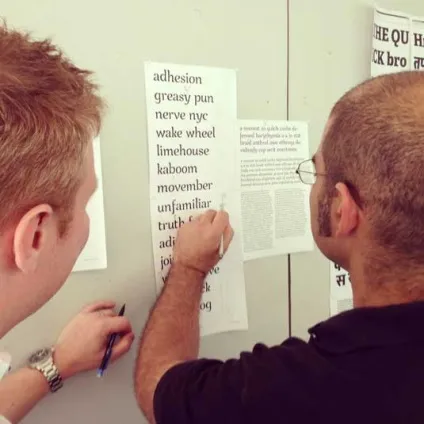
Як створити власний шрифт
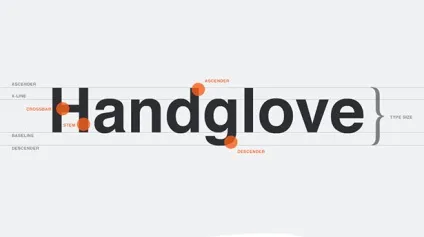
Дуже багато було написано про дизайн шрифтів, особливо про історію їх створення. Ми Новомосковсклі про безліч технік створення шрифтів. Але звідки, власне, потрібно починати? Якщо ви - дизайнер або ілюстратор, і ця дисципліна вам в новинку, то з чого ж вам починати?
Ми знайшли деяку корисну інформацію, але так як вона була розкидана по безлічі джерел, ми вирішили зібрати все воєдино.
1. Почніть з брифа
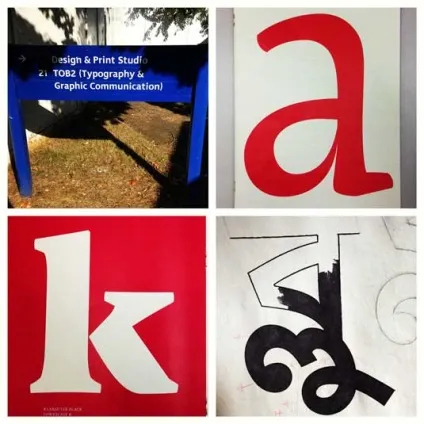
Створення шрифту - це довга і копітка робота, тому дуже важливо мати чітке розуміння того, яким має бути цей шрифт.
Розробка брифа безумовно потребують досліджень і роздумів. Як буде використовуватися ваш шрифт: він знадобиться для специфічного проекту або для особистого користування? Чи є проблема, яку ваш шрифт вирішив би? Чи впишеться ваш шрифт в масив схожих дизайнів? Що робить його унікальним?
Варіантів багато. Шрифти можуть бути створені, наприклад, спеціально для академічних текстів або заради плакатів. Тільки коли ви будете знати, як ваш шрифт може бути використаний, тоді ви будете готові починати дизайн.
2. Фундаментальний вибір
Існує кілька рішень, про які потрібно пам'ятати. Чи буде це рубаний шрифт або із зарубками? Чи буде він грунтуватися на рукописному тексті або буде більш геометричних? Чи буде шрифт створений для тексту і підходити для довгих документів? Або може він буде відображати текст в креативному стилі і буде краще дивитися у великому розмірі?
Підказка: Передбачається, що дизайн рубаного шрифту дається початківцям складніше, так як можливості таких шрифтів більш специфічні.
3. Підводні камені на ранніх етапах
Є кілька підводних каменів:- Ви можете вирішити починати з комп'ютеризації рукописного шрифту, що може бути корисним практичним вправою. Але через те, що почерк дуже індивідуальний, ваш шрифт може не мати великого успіху через свою специфічність.
- Не варто брати за основу існуючі шрифти. Переробивши трохи вже знайомий всім шрифт, ви не створите шрифт краще і не розвинете свої навички.
4. Використовуйте свої руки
Спробуйте створити красиві форми перших декількох букв на папері, а вже потім починайте комп'ютерну роботу. Наступні букви потім можуть бути сконструйовані на основі існуючих форм, відповідно до ключовими особливостями.
Підказка: Вручну зазвичай виходить намалювати більш гладкі і точні криві. Щоб було зручніше, не бійтеся повертати аркуш паперу так, як вам потрібно.
5. З яких символів почати
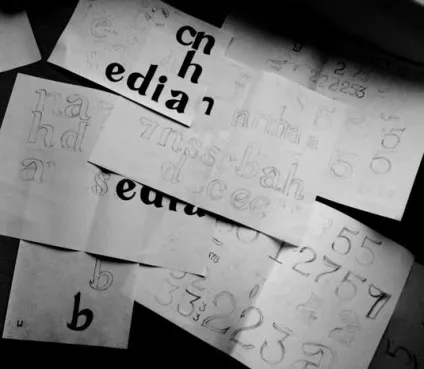
Створення спочатку певних символів може допомогти вам задати стиль свого шрифту. Ну а потім ці символи будуть використовуватися у якості направляючих. Зазвичай «контрольні символи», як їх називають, в латиниці - це n і o, а заголовні - H і O. Найчастіше використовується слово adhension, яке допоможе протестувати базові пропорції шрифта (але, деякі пишуть це слово як adhencion, тому що буква s може бути дуже підступною).
6. Переносимо шрифт на комп'ютер
Існує безліч способів перенести малюнок на комп'ютер. Деякі рекомендують трасувальні програми, але багато хто воліє здійснювати цю роботу вручну, щоб мати повний контроль над точками і формами.
Багато програм потребують чіткого та яскравому малюнку, тому як тільки вам сподобався ваш шрифт, обведіть його тонкою ручкою і заповніть форми маркером.
Підказка: Якщо ви обробили намальований шрифт так, як було описано вище, то ви можете просто зробити фото малюнка і працювати з ним.
7. Вибір програми
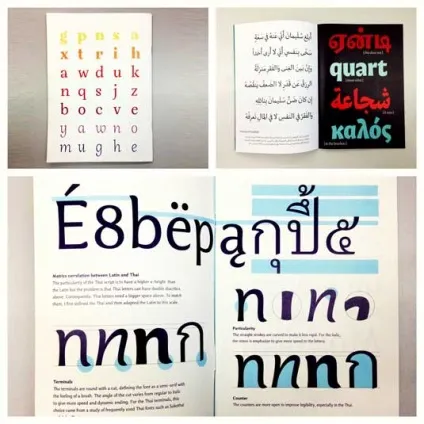
Багатьом дизайнерам подобається використовувати Adobe Illustrator. Для малювання окремих форм та експериментування він відмінно підходить. Але надалі стає очевидним, що для створення шрифтів він не підходить. Вам захочеться працювати з програмою, яка дозволить працювати з інтервали між буквами і створенням слів.
Відмінна програма - FontLab Studio, але новий софт, такий як Glyphs і Robofont набирають все більшої популярності. Ці програми недешеві, але у Glyghs є «міні» версія в Mac App Store з деякими відсутніми функціями, що не дуже добре, тому що ці функції важливі новачкам.
8. Використання програми
Не забувайте розташувати крайні точки буквених форм (верхня, нижня, права, ліва), щоб краще контролювати процес.
Коли ви закінчили всі роботи по згладжування форм, подивіться, як він виглядає в повноцінному тексті. Візьміть собі за мету проаналізувати те, як шрифт виглядає в рядку, абзаці і так далі. І не варто чекати, поки ви зробите весь алфавіт.
Цей онлайн-інструмент допоможе вам створити текст з тих букв, які у вас вже є.
Дуже важливо подивитися, як ваш шрифт буде виглядати в різних розмірах. Слідуючи своєму брифу, оцініть вийшов шрифт, подивіться, чи можна прочитати текст, якщо виставити малий розміру шрифту.
Ви повинні зрозуміти, як ваш шрифт буде себе вести при зміні його розміру. І так, це може створити масу проблем, але ви ж не хочете видавати сирої результат.
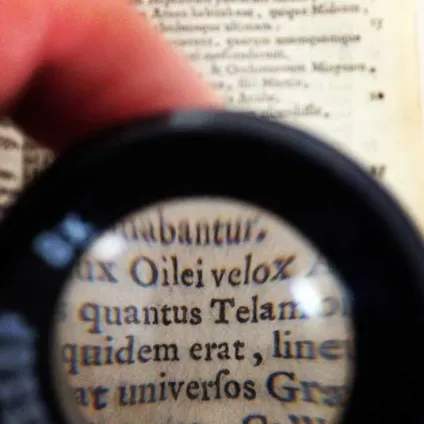
Роздрукуйте свій шрифт і прискіпливо оціните його вид на папері. Набагато простіше побачити будь-які недоліки, якщо ви прикріпіть лист на стіну, наприклад, і подивіться на шрифт здалеку.
Ще один онлайн-інструмент (також майже 10 доларів за скачування), який дозволяє створювати шрифт з тексту, написаного від руки.